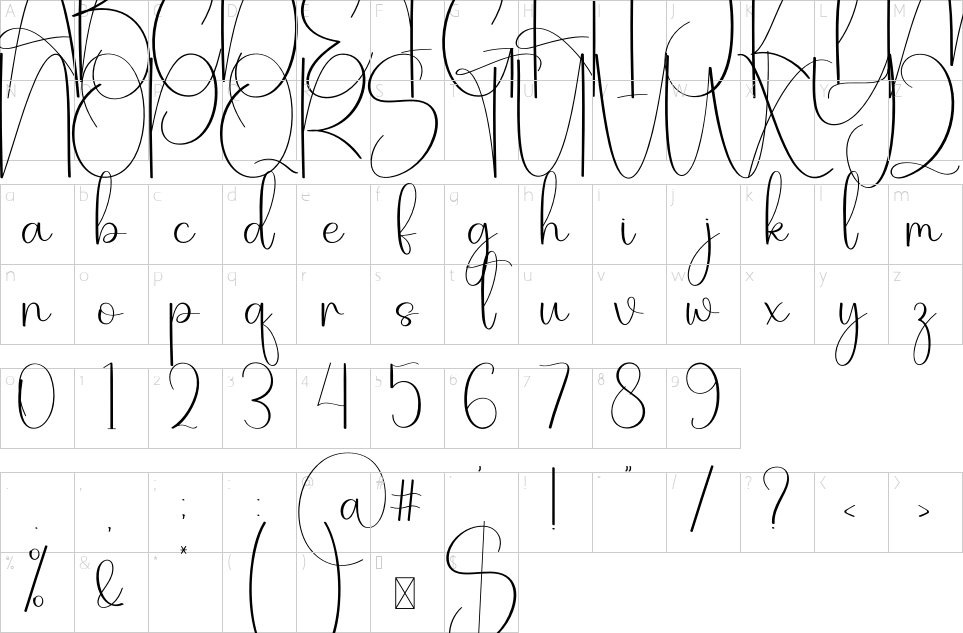
Daddy Signature Font
Aqui está uma descrição envolvente para a página de download da fonte ‘Daddy Signature Font’, seguindo as instruções: ‘Introduza seu estilo único com Daddy Signature, uma fonte original criada por scratchones e disponível gratuitamente tanto para Windows quanto para Mac. Esta fonte leva um toque de personalidade ao seu design digital, se tornando o acessório perfeito para criar mensagens memoráveis. Descubra como sua escrita adquire vida com a Daddy Signature, transmitindo uma aura autêntica e sofisticada. Com 441 downloads já contabilizados, é evidente que essa fonte está ganhando popularidade por seu design único e versatilidade. Não perca tempo, baixe sua cópia de Daddy Signature agora para dar um toque especial em seus trabalhos digitais.’
Mapa de caracteres da fonte Daddy Signature Font